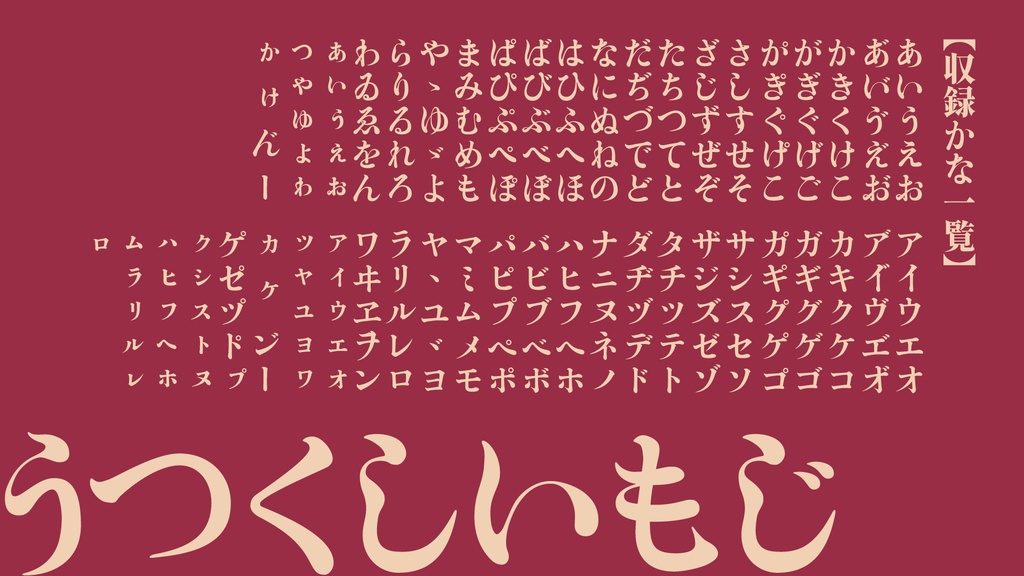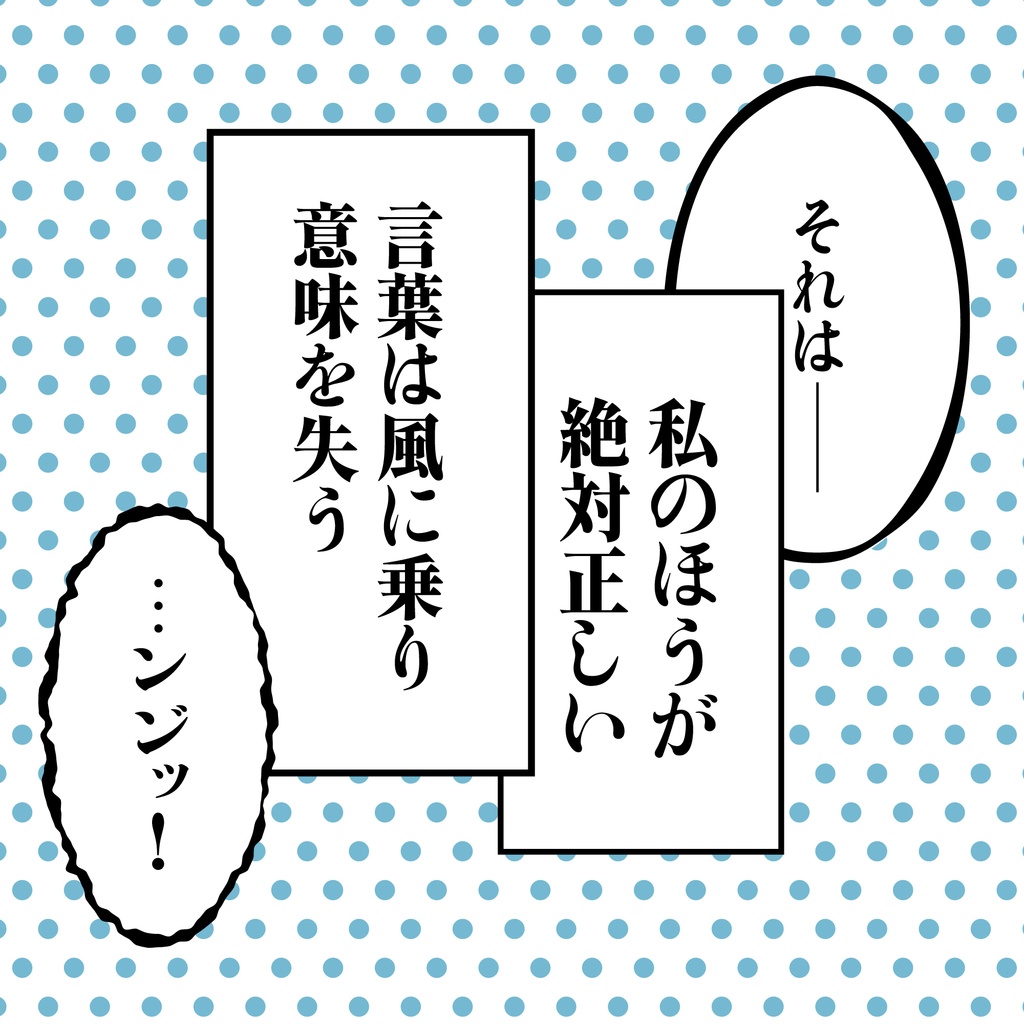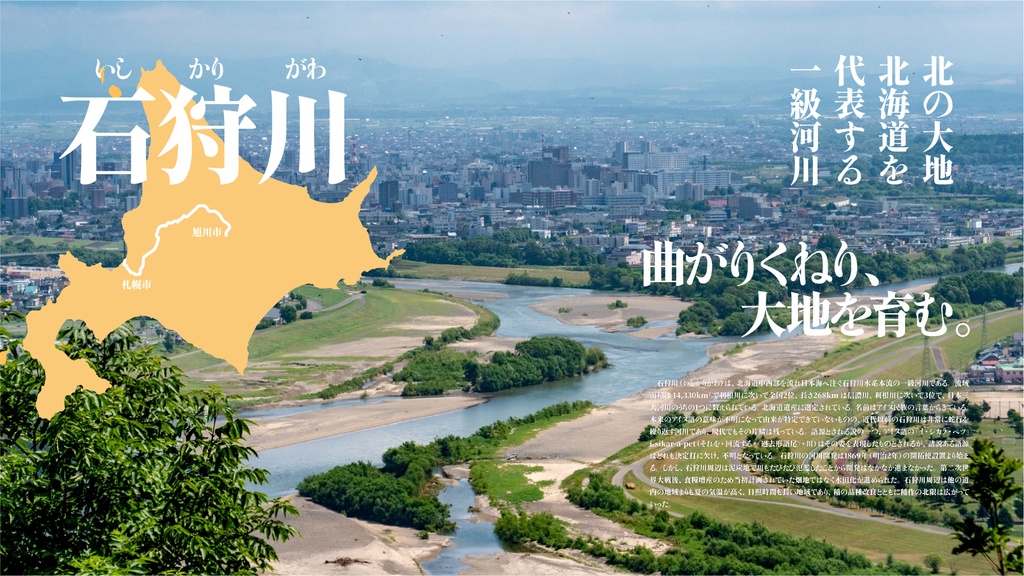
【フリーフォント】築豊初号明朝OFL│見出し向け明朝体
■書体概要 見出しやタイトルなど目立たせたいところに向いたオールドスタイルの明朝体です。伝統的な築地初号の流れを汲む、「築豊初号見出しかな」を元にブラッシュアップされた仮名とどっしりとした骨のある筆脈が特徴です。 漢字には角立て処理の施されている源ノ明朝の派生フォント「源流明朝2.100」を利用しています。 オリジナルのフォントに深く感謝いたします。 ■収録文字 ひらがな、カタカナ、漢字、一部記号・役物、欧文(英語) ■ご利用にあたり SILオープンフォントライセンスでの配布なので、商用・個人利用可能です。 2024/12/25 公開 2025/01/05 フォント名の文字化けを修正 2025/07/29 和文フォントとして認識されない問題を修正 Copyright (c) 2025 Typographish All Rights Reserved.